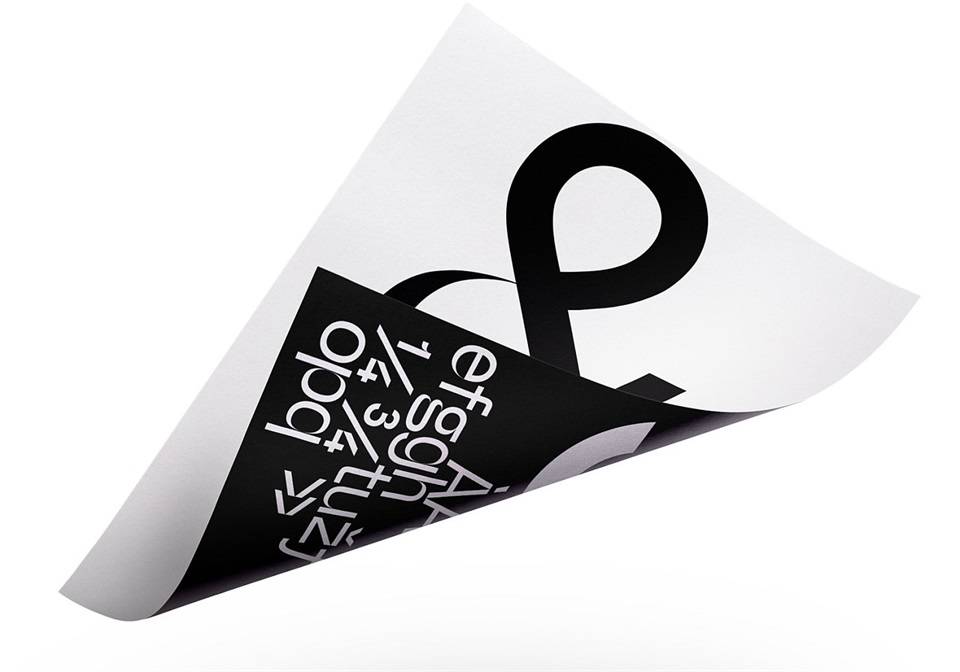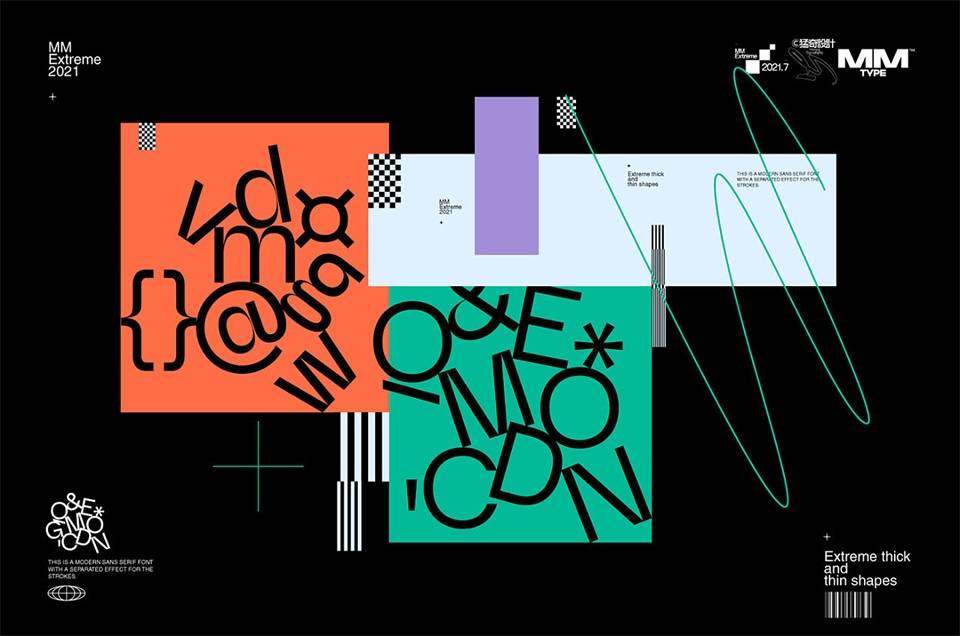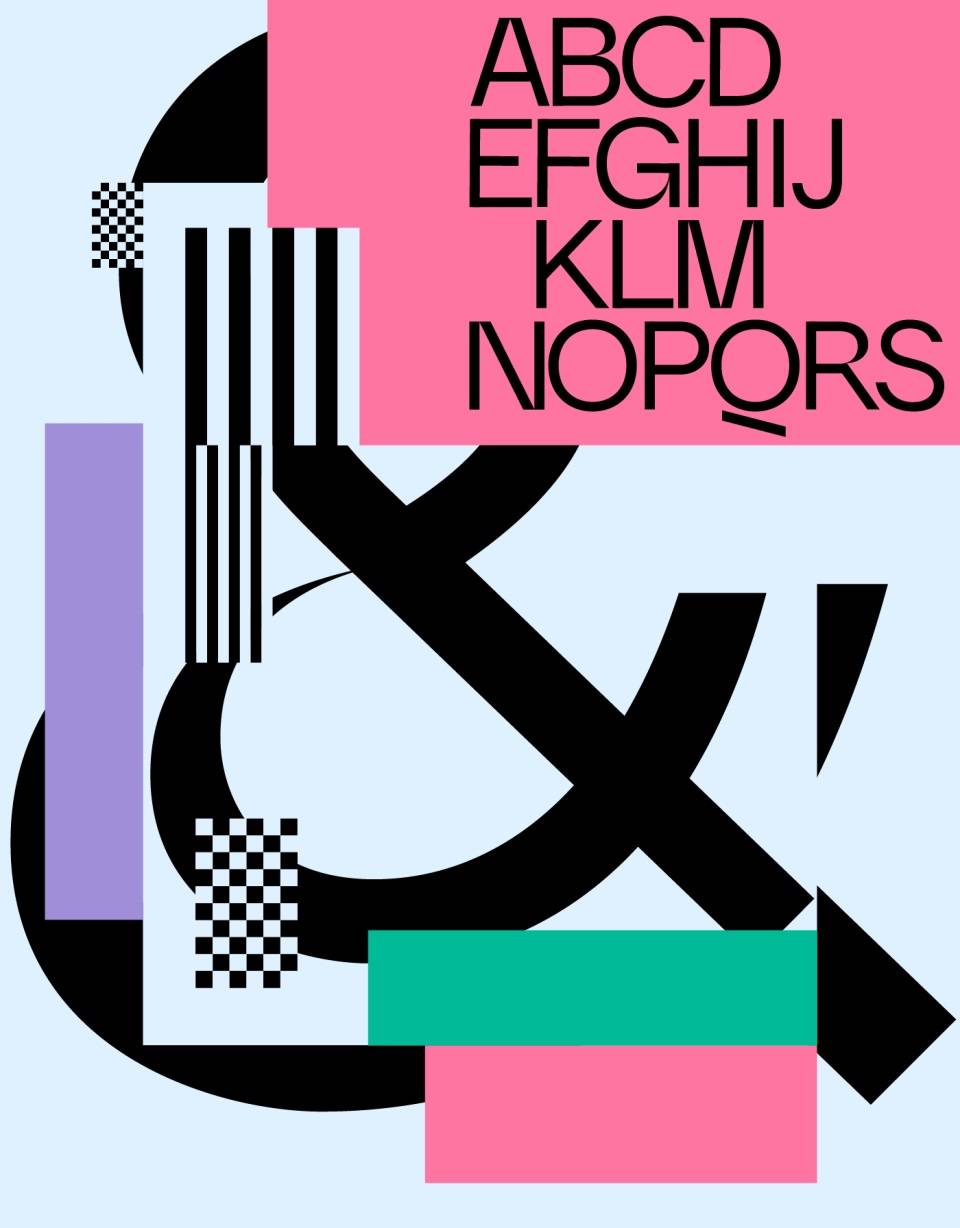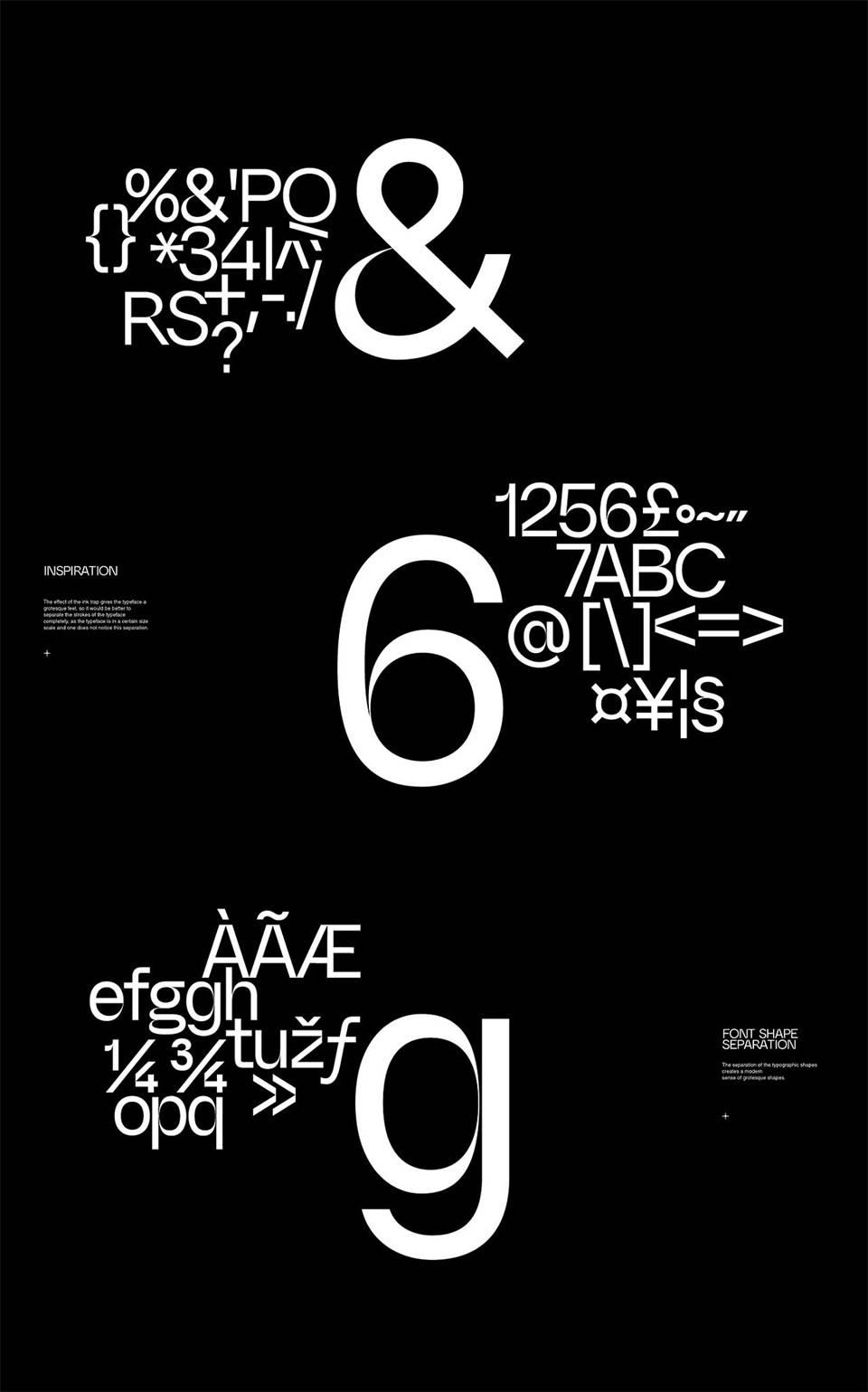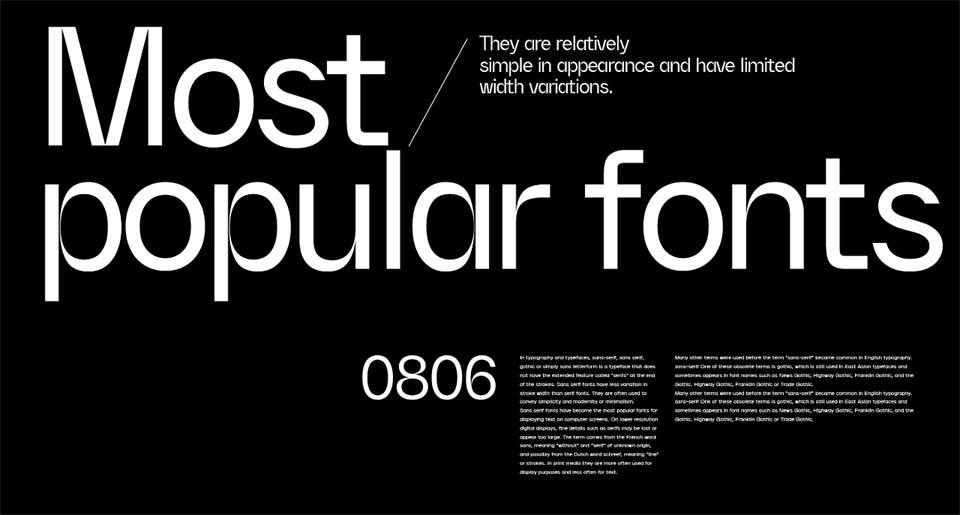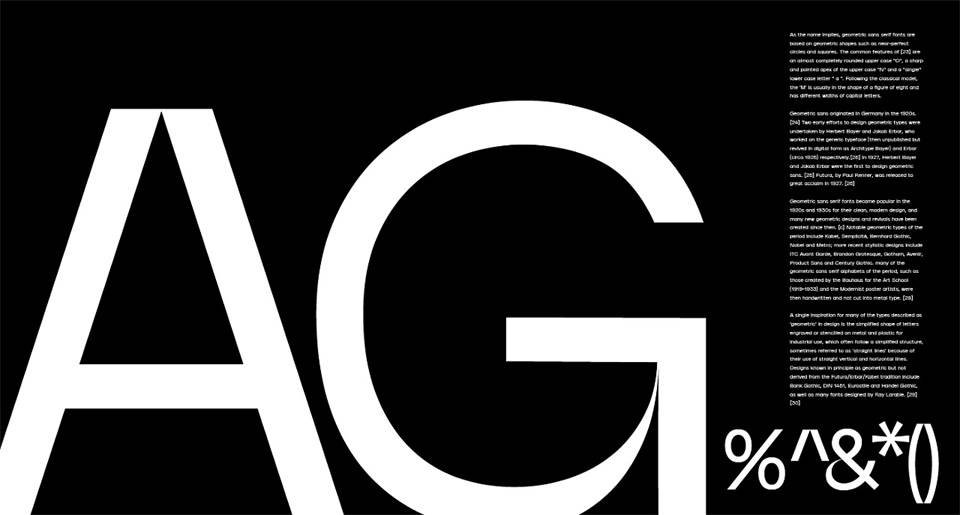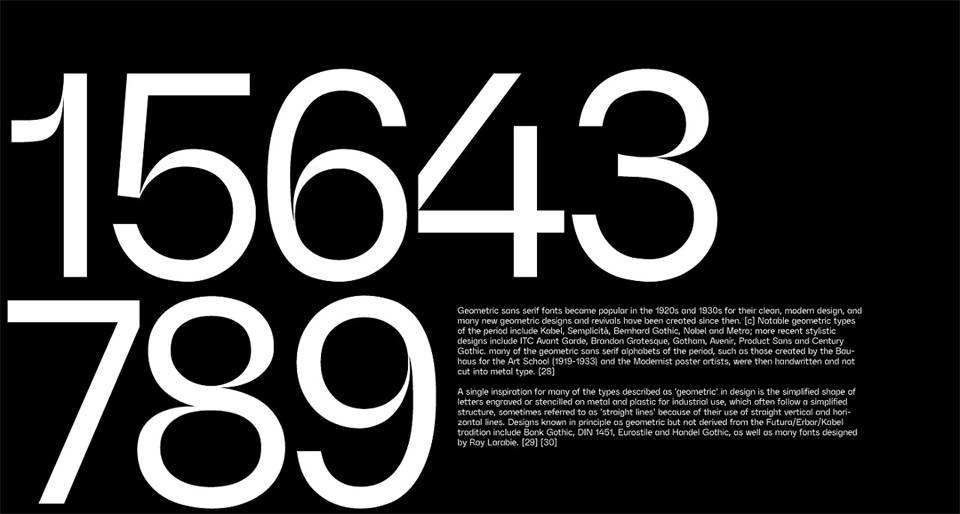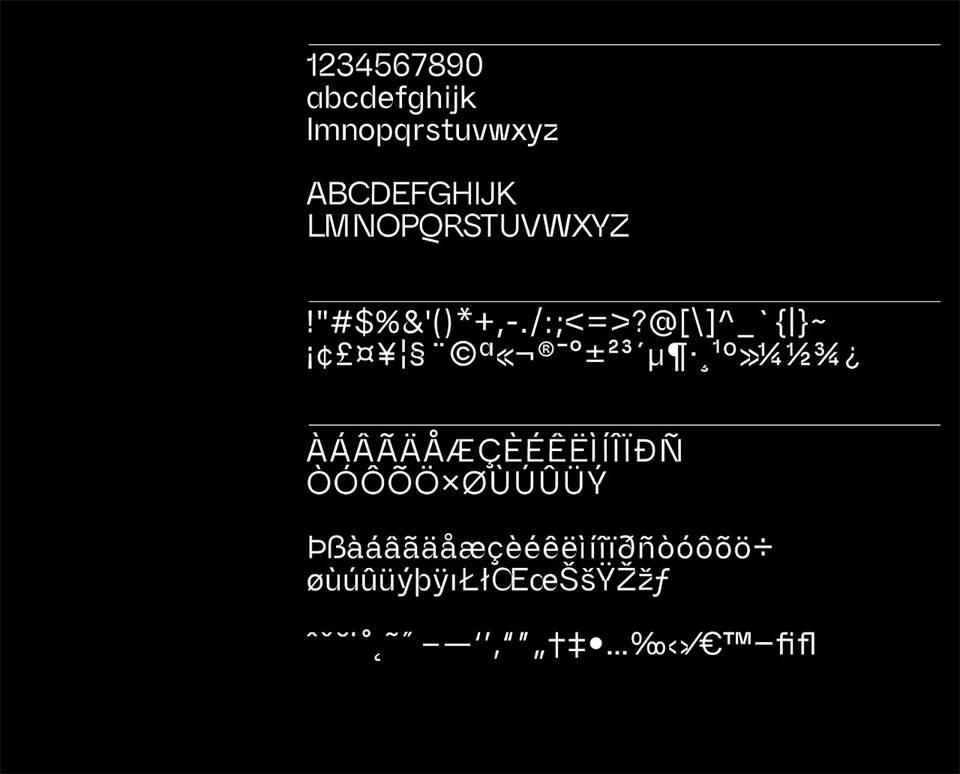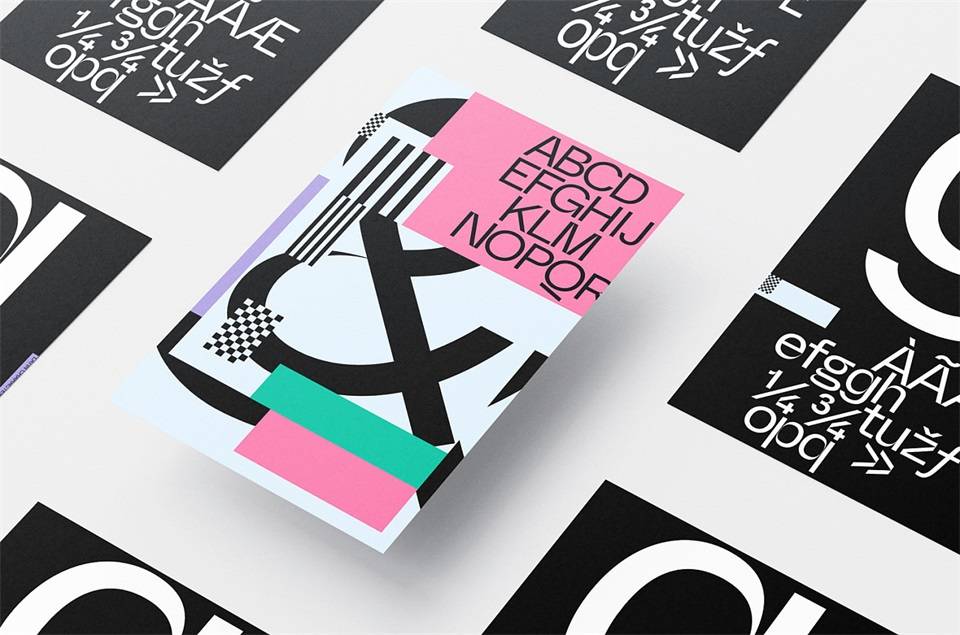
字体风格介绍:
这是一款现代无衬线字体,采用扁平的形式和笔画分离的处理方式。大段文字的编排效果良好,用作大标题时则有锋利而夸张的笔触形态。
字体放大后充满了错觉,这种奇特的风格为字体设计增添了风格。
它可以用于正文布局,以及超大的标题。
字体名称:MM Extreme
“MM Extreme”是一款书写很新颖的字体,字体大方,适合各种设计作品使用!欢迎下载!